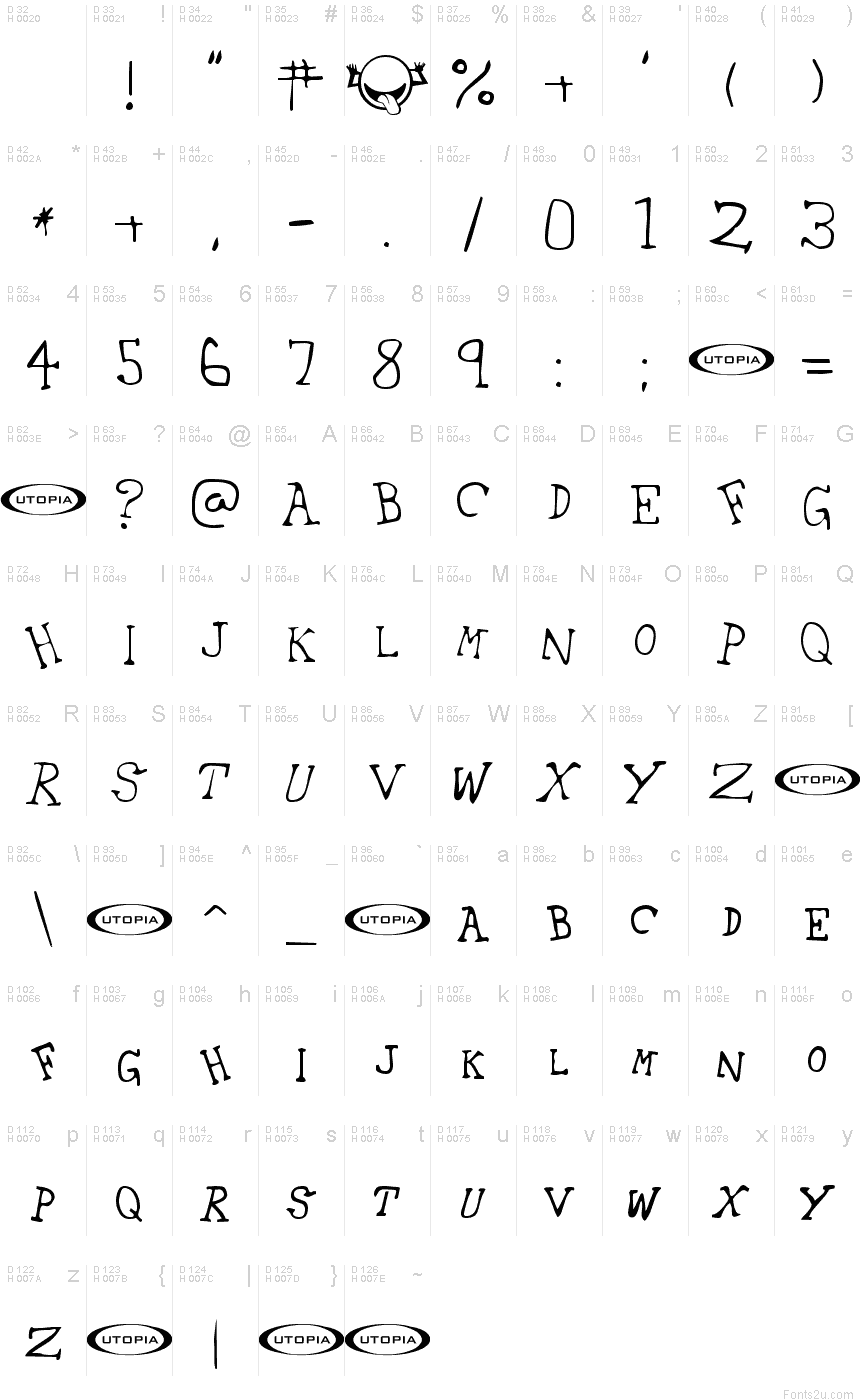
خط 42 Emancipated من Utopiafonts هو خط عرض مجاني ومشوه، بحروف تبدو وكأنها مُطت ولوُيت وثُبتت يدويًا. تميل الأشكال الطويلة والنحيلة بزوايا غريبة، مع ضربات حبر غير متساوية تمنح انطباعًا بالمرح والاضطراب في آنٍ واحد، وكأنها ملاحظة مكتوبة بخط اليد من عالم حكايات خيالية ملتوٍ. إيقاع الخط حر ومضطرب، مما يجعل كل كلمة تبدو حية بدلاً من أن تكون مُصممة بشكل آلي.
باستخدام 42 Emancipated، ستكتسب عناوينك فورًا طاقة غريبة وغير تقليدية تخطف الأنظار من النظرة الأولى. هذا الخط المجاني يتألق على ملصقات الحفلات، وأغلفة الكتب التجريبية، والمجلات، وتصاميم الرعب والكوميديا، وفعاليات الهالوين، وأغلفة الألبومات التي تحتاج إلى طابع "غريب وجميل". ادمجه مع خط بلا زوائد (sans serif) هندسي ونظيف في الأحجام الصغيرة للحفاظ على القراءة، واترك لـ 42 Emancipated مهمة العناوين الصاخبة والفوضوية.